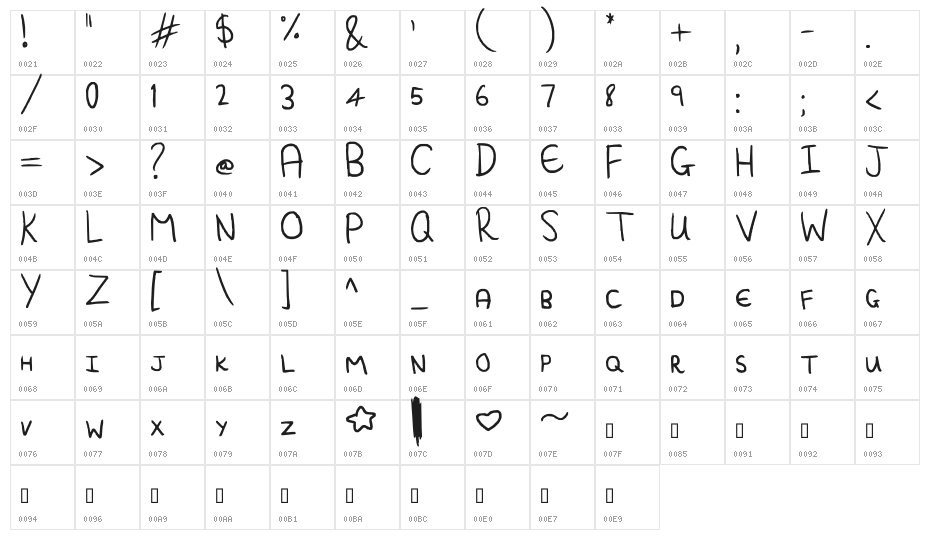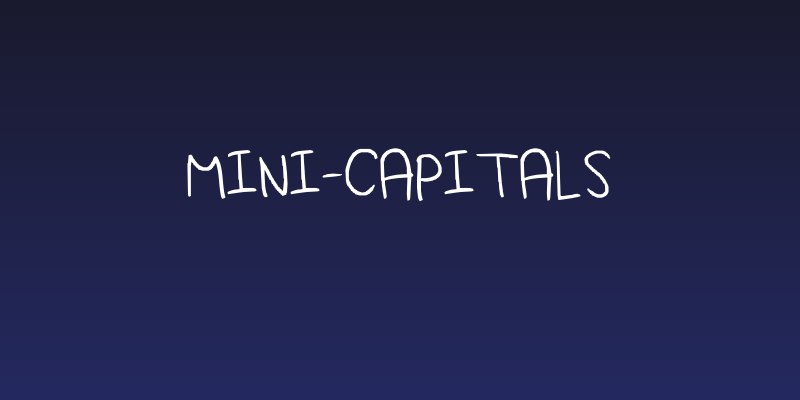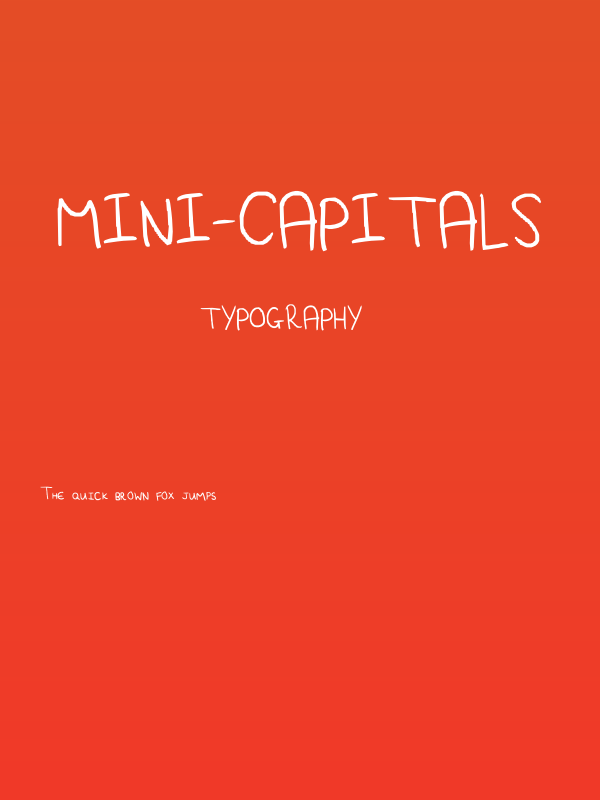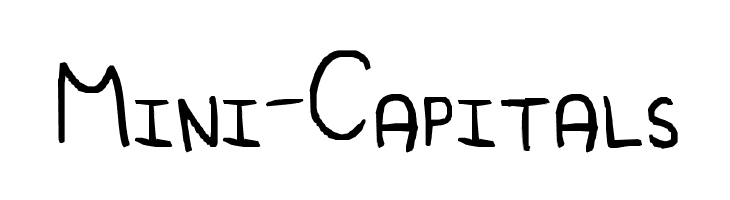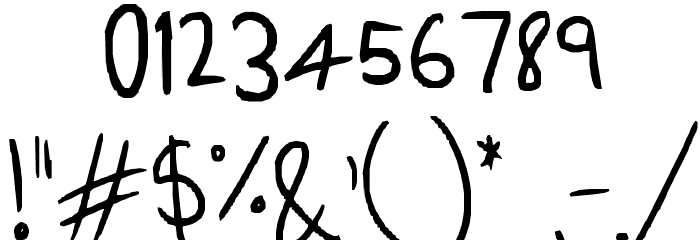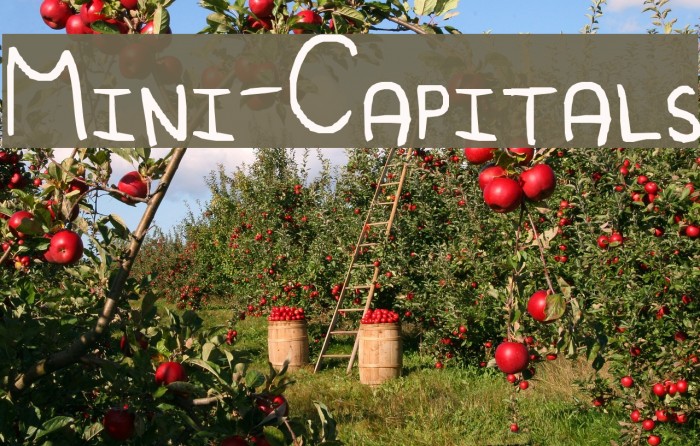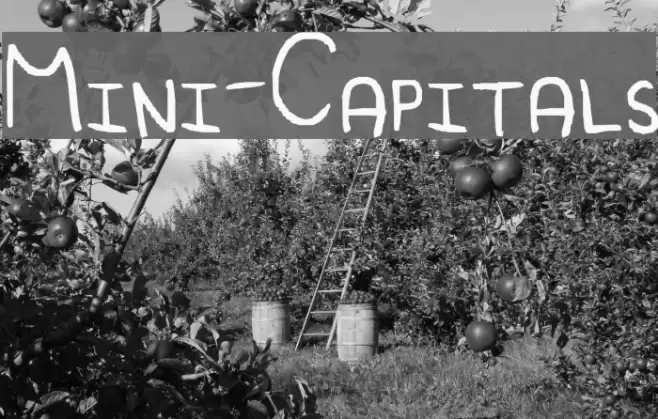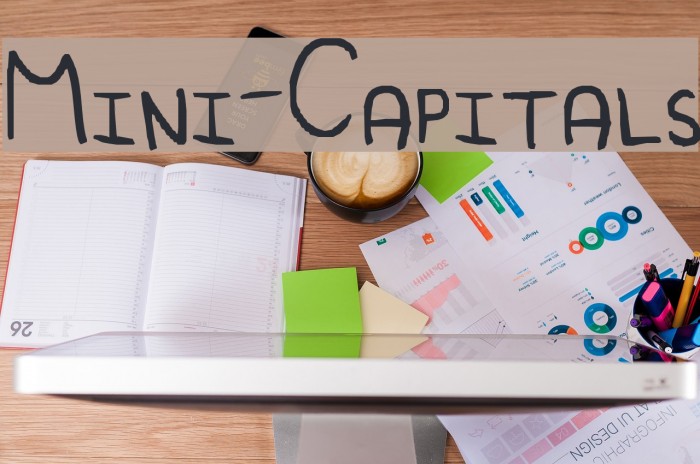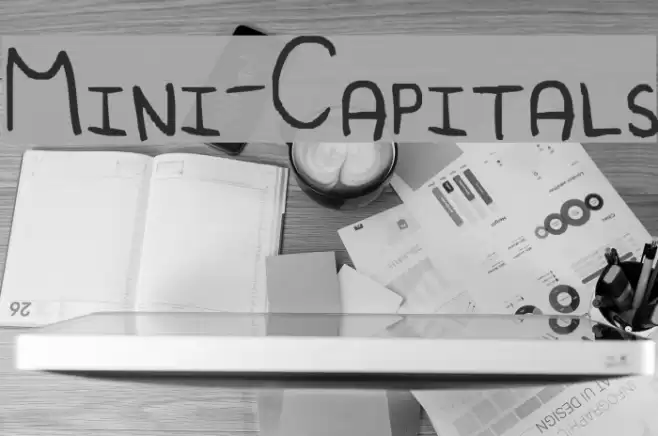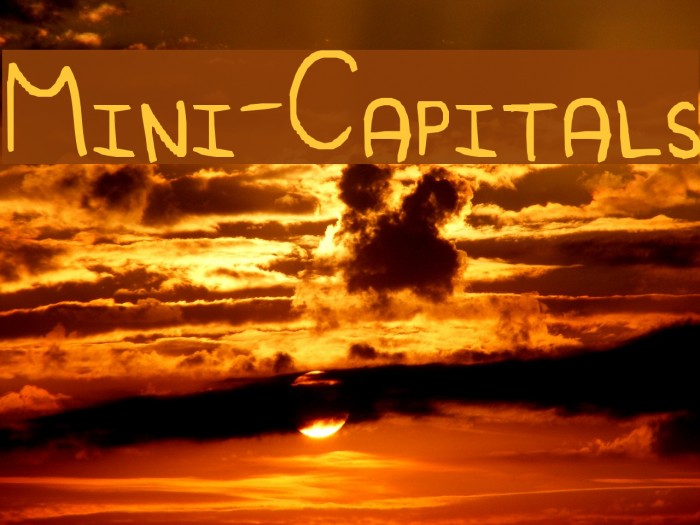
Mini-Capitals Font
✎ Handwritten
| श्रेणियाँ | Handwritten |
| समग्र शैली | Casual |
| उपयोग का मामला | Logos, Headlines, Informal Invitations |
| सुझाए गए प्रोजेक्ट | Ideal for greeting cards, children's books, casual branding, and playful social media graphics. |